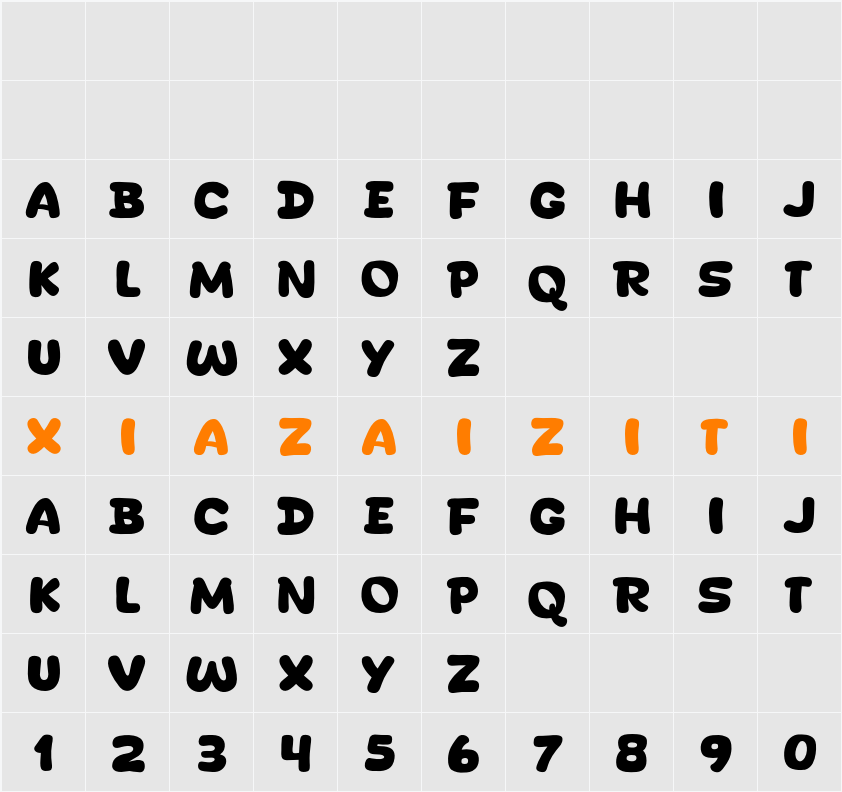
Willkids
Willkids,这款字体结构工整、笔画清晰,兼顾美观与易读性,适用于标题、正文、海报、包装、LOGO 等多种场景。字形优雅稳定,风格百搭耐看,适配日常排版与创意设计,让文字呈现更舒适、更具质感。Willkids一笔一画,皆是细节,以均衡的比例、流畅的线条打造舒适视觉体验,字形端正大气,风格简约现代。无论是商业设计、品牌宣传还是日常排版,都能轻松驾驭,让文字更有格调与力量。Willkids字体下载。
• 设计师: Khurasan